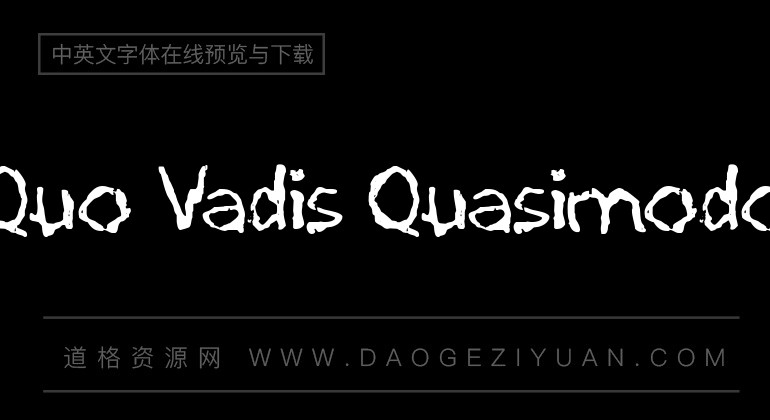
Quo Vadis Quasimodo 是一种手写风格的字体,具有优美的字母结构和流畅的笔画。它最初由意大利设计师Gabriele Di Carlo在2011年创建,灵感来自于文艺复兴时期的手写体。该字体包含了大写字母、小写字母、标点符号和数字,适合用于海报、广告、书籍、印刷品和网页设计等各种设计项目。 此字体的特点是线条柔和,笔画流畅,字母之间距离适当,让人感觉舒适自然。它的笔画末端呈现出一种独特的锯齿形状,使得字母的外观更加生动有趣。该字体还有一些变种字形和字母连写,可以让设计师更加灵活地运用。它的字体格式包括TrueType和OpenType,可以在Windows和Mac操作系统上使用。内容介绍
Quo Vadis Quasimodo是一款非常不错的手写艺术字体,具有很好的视觉感,适合于文化类的宣传设计、商业类品牌的广告和产品包装设计以及个性化文字排版等较多场景。